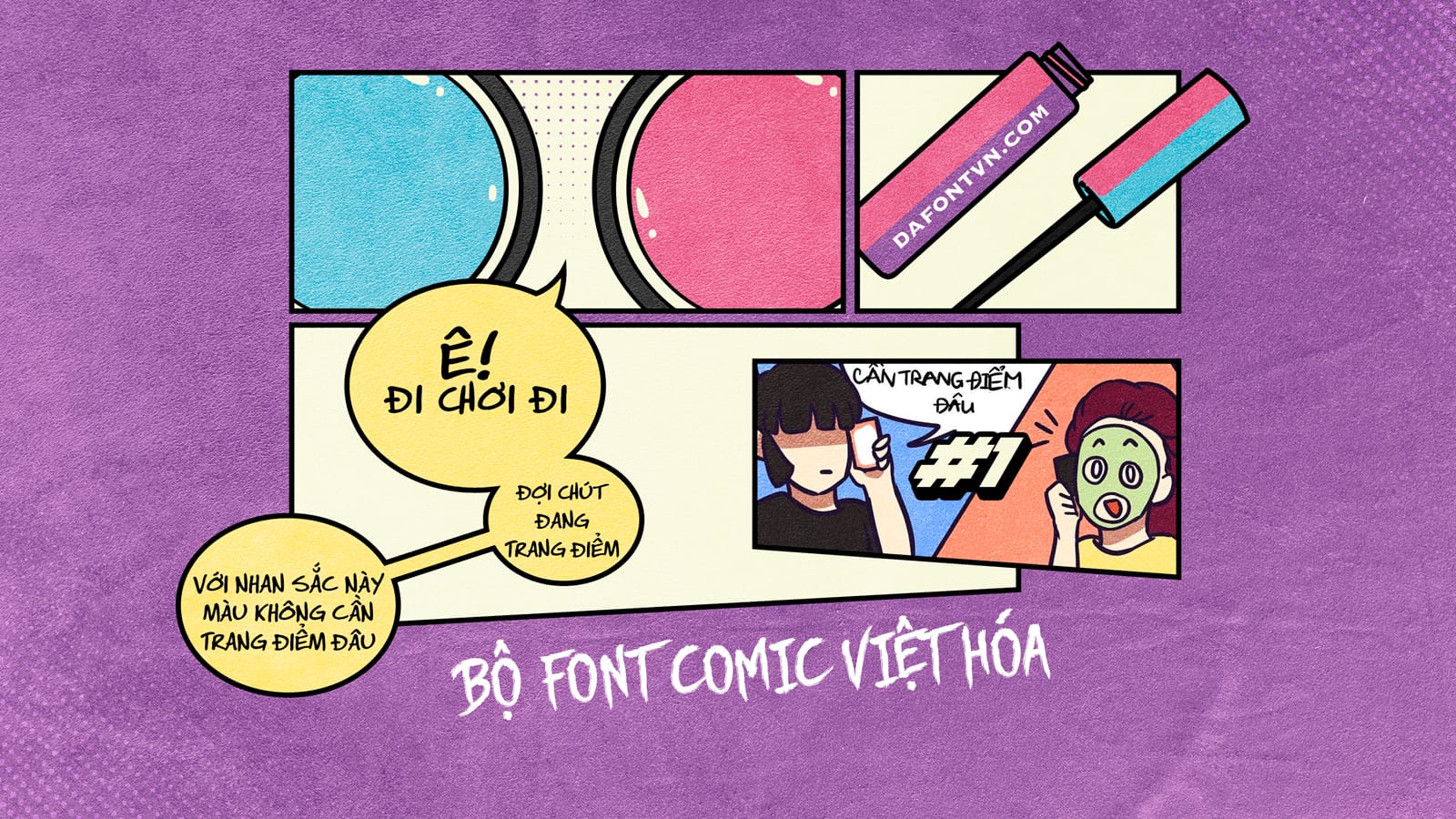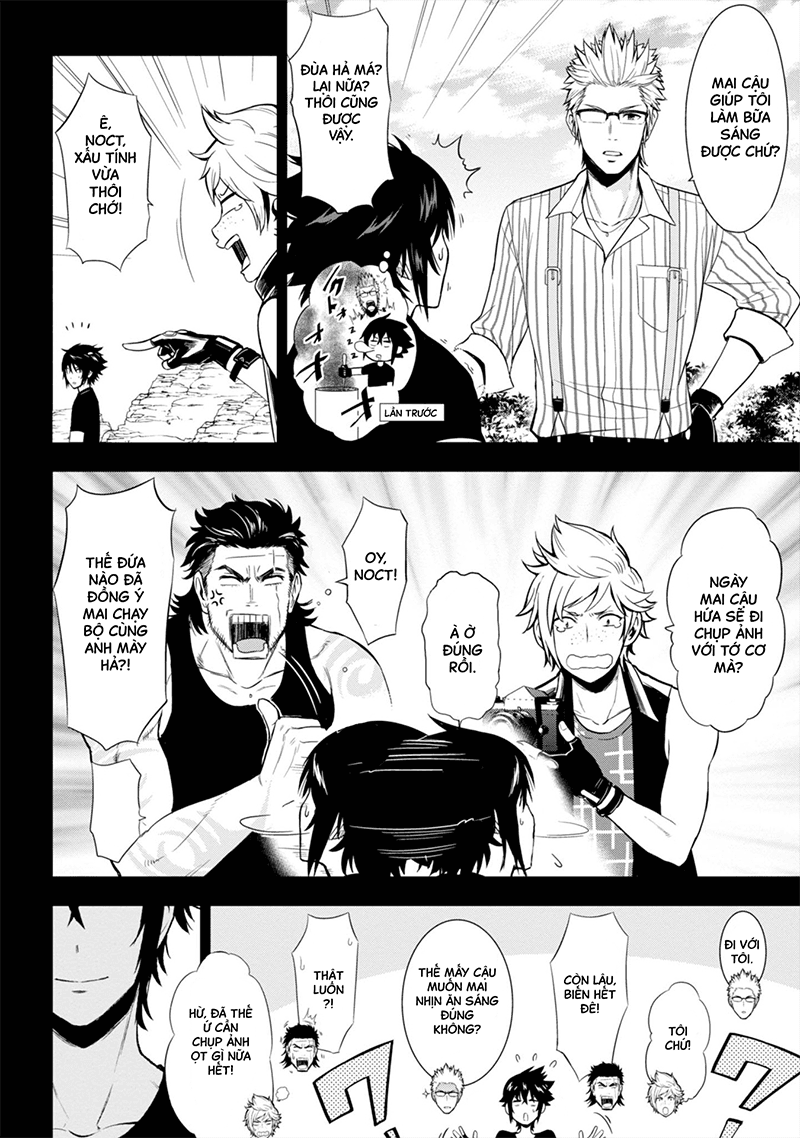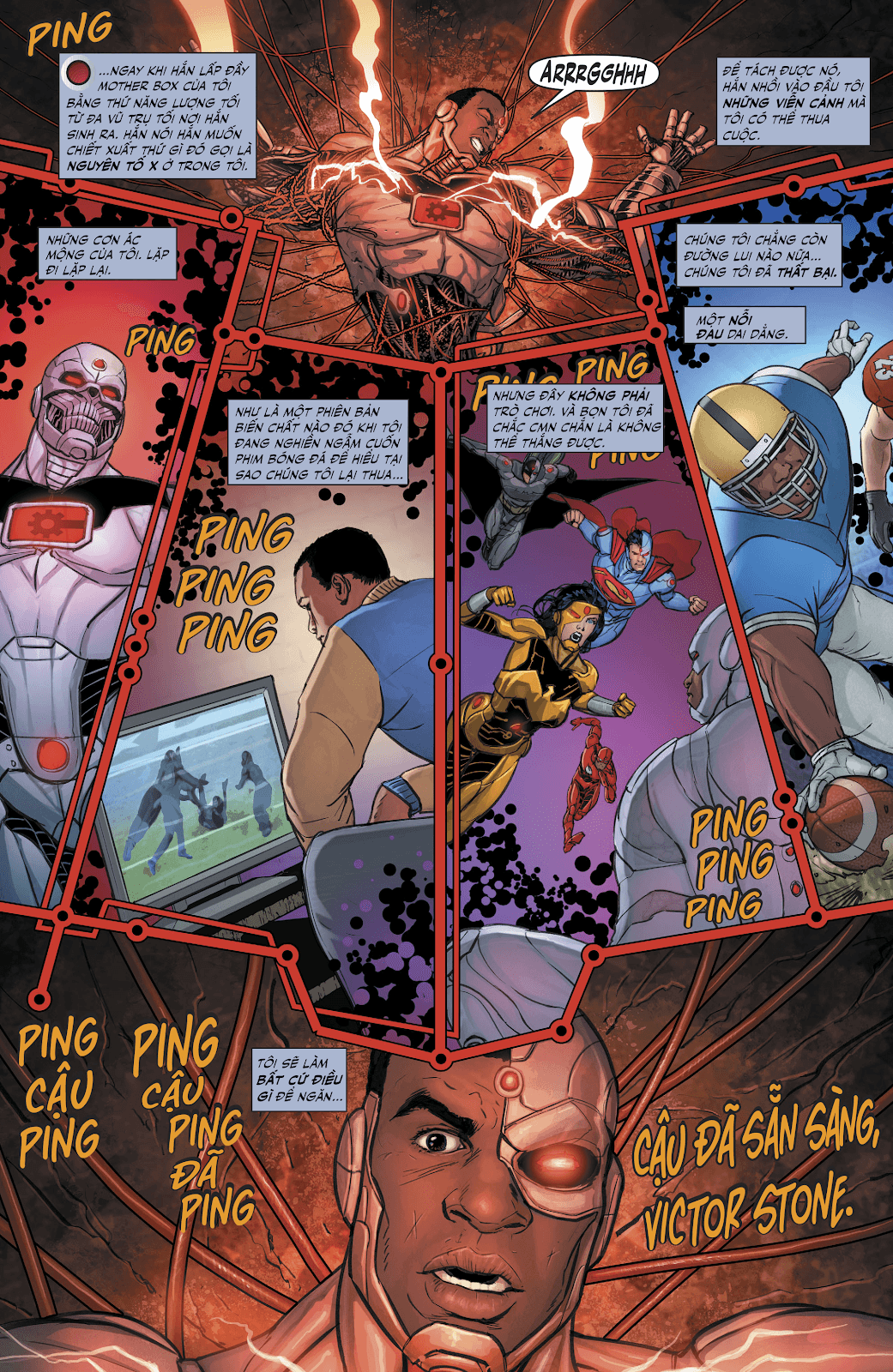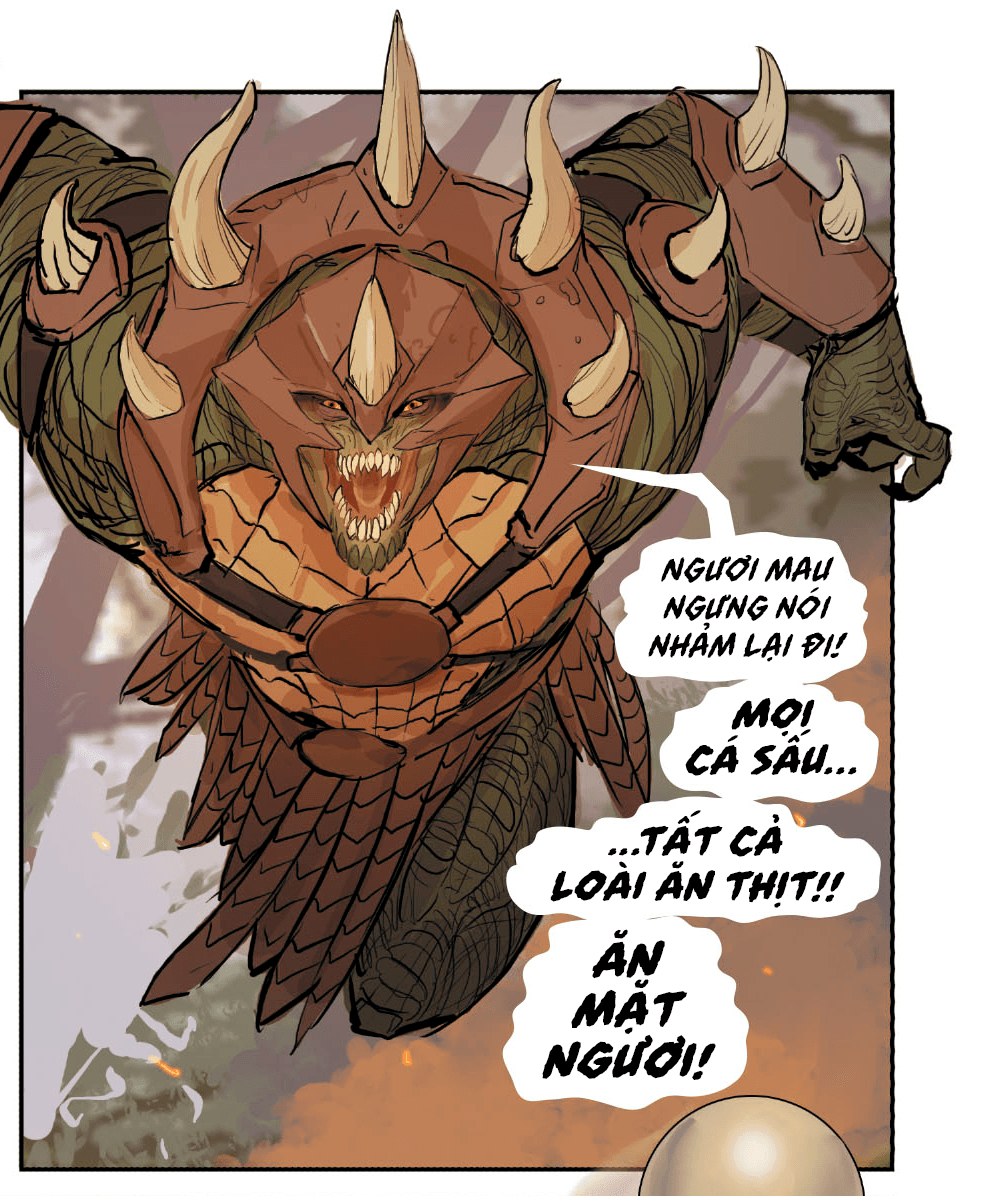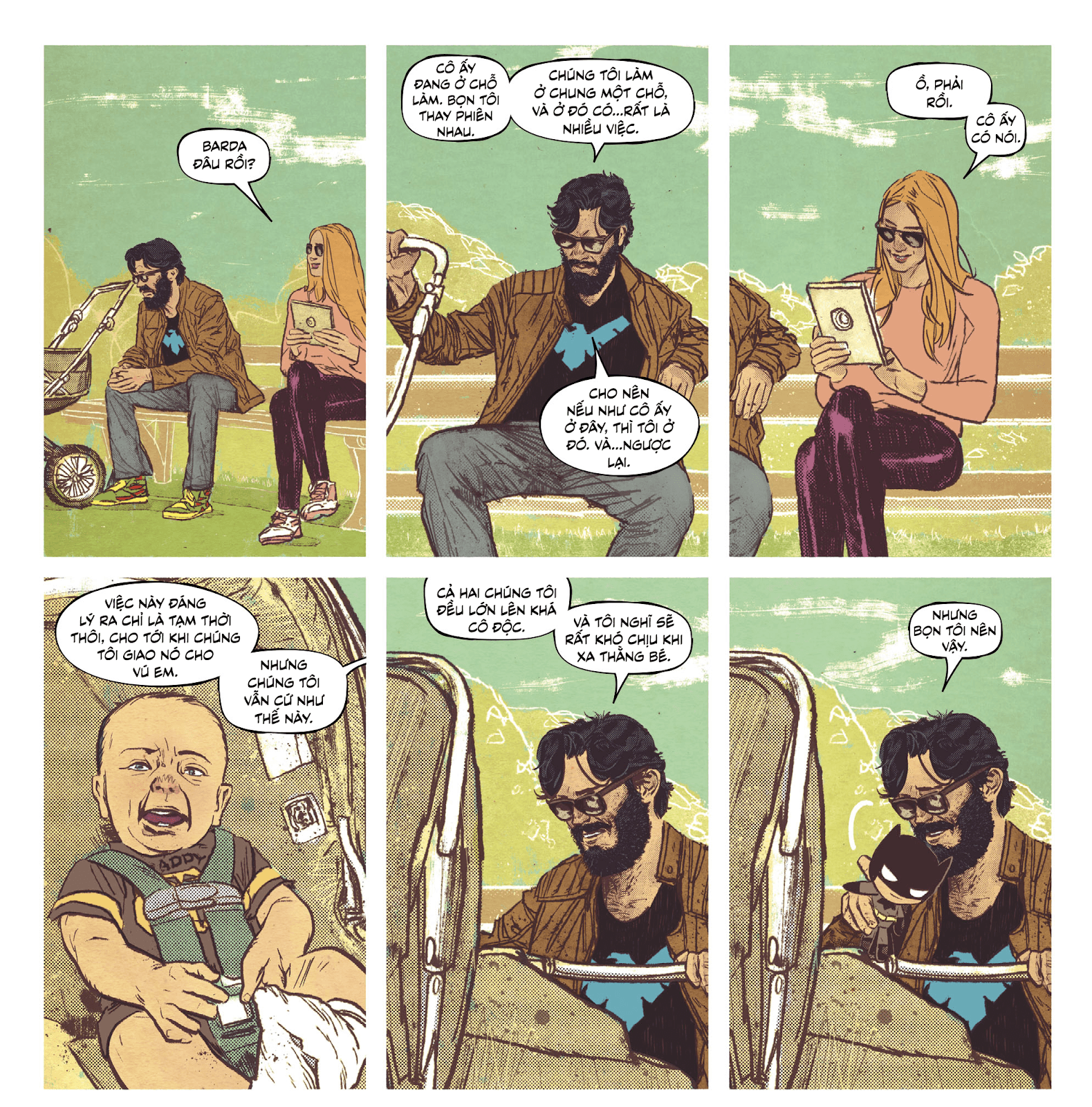
Bộ font chữ edit truyện tranh Việt Hóa siêu đỉnh
Đây là bộ font chữ của nhóm dịch Wonderland, do nhóm trưởng iCiel Việt hóa. Bộ này dành dành cho edit truyện tranh với các font hiếm mà có thể bạn sẽ không thể tìm thấy ở đâu.
Bộ font này là Teddy Bear Việt Hóa, ban đầu nó được sử dụng để phục vụ cho group, tuy nhiên sau đó nó đã được cho phép tải miễn phí để phục vụ cộng đồng. Bộ font được việt hóa theo bảng mã Unicode với hơn 100 font được việt hóa công phu và tỉ mỉ, cùng với đó là bộ font rất chất lượng do bạn Quang Bảo đóng góp.
Demo một số font sử dụng edit comic:
Font chữ edit truyện tranh Việt Hóa siêu preview 2
Font chữ edit truyện tranh Việt Hóa siêu preview 3
Font chữ edit truyện tranh Việt Hóa siêu preview 4
Font chữ edit truyện tranh Việt Hóa siêu preview 5